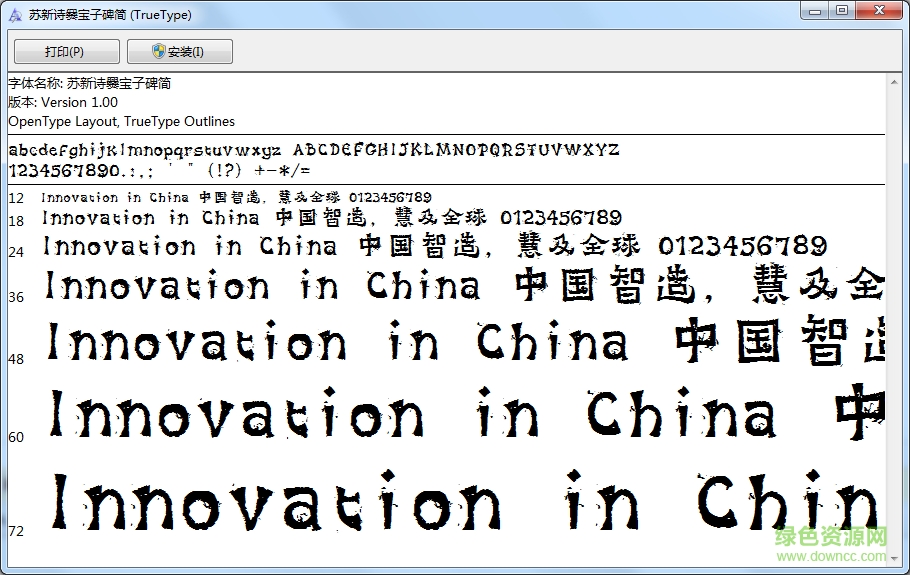
蘇新詩爨寶子碑簡體
蘇新詩爨寶子碑簡是一款簡體藝術字,文字以碑體為主,富有濃烈的碑體刻字感,字體周圍略帶點綴,少了一些正式感,顯得字體略帶休閑意味,歡迎有需要的朋友到綠色資源網(wǎng)下載使用!
應用于書法方面的簡體中文漢字,該字體以碑體為原形,筆鋒犀利,字形大小適中,并且字庫完整,整體效果十分出眾,可用于卡通設計、廣告設計、平面設計、印刷包裝、報紙雜志等行業(yè)。